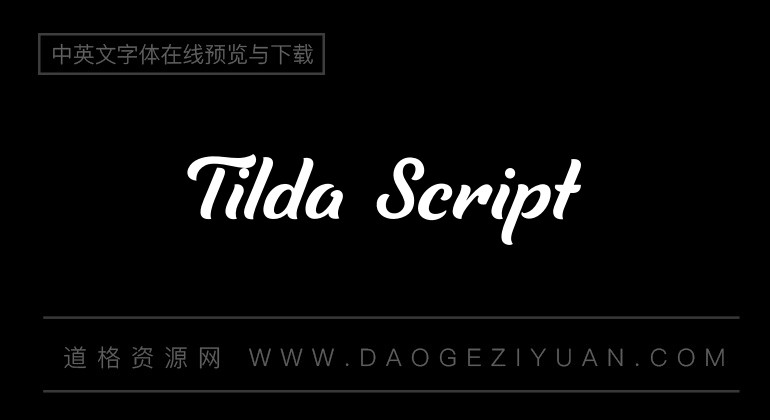
Tilda Script
? Tilda Script 是一种手写风格的字体,它拥有一种自然而优雅的外观,适合用于标题、标签、报名表和其他文字排版中。Tilda Script 的字体特点是细腻的笔画和灵活的字形,可以在设计中起到很好的视觉效果。它的字体曲线流畅,字体细节清晰,可以满足不同的字体需求。它的字体设计简洁,可以满足大多数文字排版需求,是一款非常适合用于标题、标签和其他文字排版的字体。
Tilda Script是一款非常不错的手写艺术字体,具有很好的视觉感,适合于文化类的宣传设计、商业类品牌的广告和产品包装设计以及个性化文字排版等较多场景。